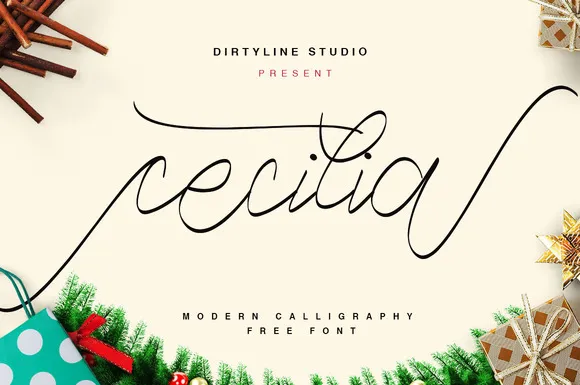
Cecilia Script Font – Download Grátis
A Cecilia Script é uma fonte elegante que captura a essência das obras de arte do calligrafista. Com linhas suaves, base vertical dançando e uma aparência clássica e sofisticada, esta fonte foi projetada para diversas aplicações, desde títulos em grandes cartazes até detalhes sutis em selos de correspondências ou etiquetas. Suas 394 glifos e 224 alternativas permitem que você personalize seus materiais com flexibilidade. Ela se adequa perfeitamente a estilos variados, incluindo assinaturas, identidade visual de empresas, cartões de aniversário, selos em produtos, mensagens informativas, outdoors e até mesmo elementos para camisas personalizadas. Ideal tanto para designers como para aqueles que desejam um toque de criatividade em projetos pessoais, a Cecilia Script é uma escolha perfeita se você está procurando por uma fonte com estilo único. Ela traz uma dose extra de sofisticação às suas criações, deixando-os não apenas legíveis, mas também memoráveis.